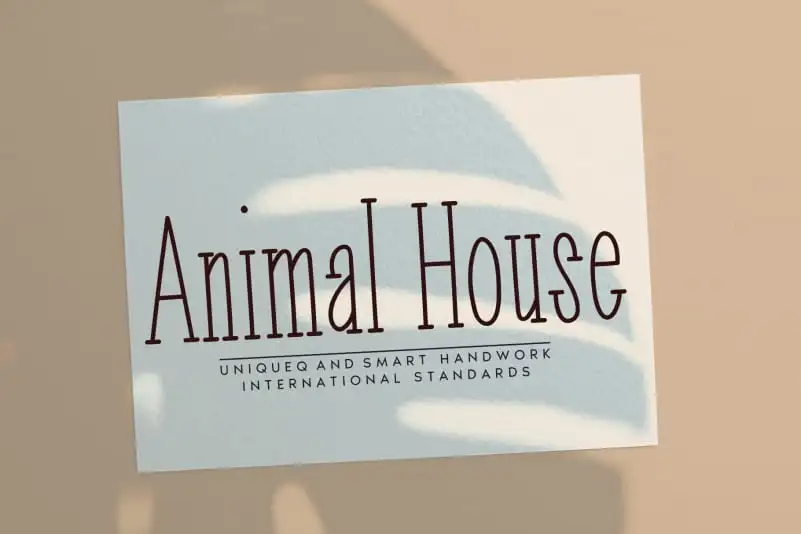
Animal House Display Font
Descubra Animal House Display Font, uma elegante novidade para designers digitais do Brasil. Especialmente criada para aqueles que procuram algo único e diversificado na categoria de fonts manuscritas, esta fonte oferece um toque autêntico e vibrante à sua arte digital. Ideal para criar texturas animais em diversos formatos, a Animal House Display Font é perfeita para projetos criativos envolvidos em estilos imersivos. Seja para publicações de design gráfico ou obras digitais cheias de personalidade, ela estará sempre pronta para transformar seu trabalho numa verdadeira obra-prima. Ideal para designers brasileiros à procura de algo que combine originalidade com um toque autoral, Animal House Display Font é uma escolha perfeita. Sua linguagem concisa e informativa não só promove a compreensão da fonte, mas também desperta o interesse dos leitores em suas possibilidades. Criada pelo designer andikastudio, esta fonte atende com excelência os requisitos de quem busca um produto verdadeiramente inovador. Seja para aplicar à identidade visual de uma marca ou a personalizar conteúdo online, Animal House Display Font fará sua arte digital soar extraordinariamente única e especial.